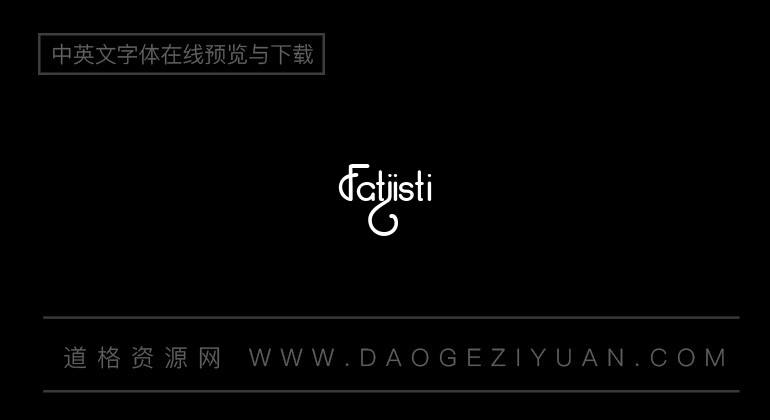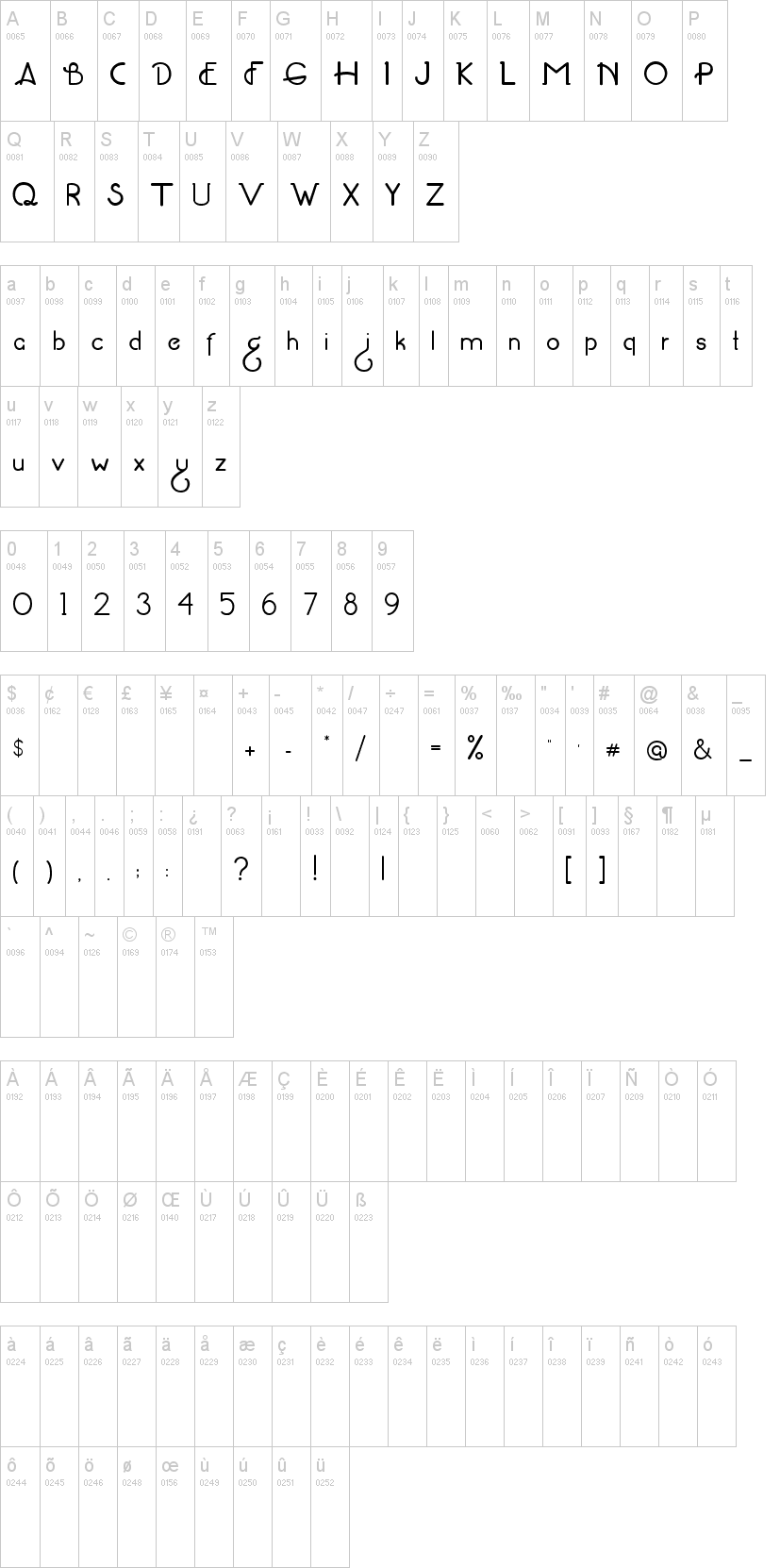
Fatjisti 字体是一款简洁、优雅的英文字体,它的特点是字体的线条粗细比较均衡,没有太多的变化,给人一种稳重、大气的感觉。Fatjisti 字体有英文、拉丁文、希腊文等多种字体,适用于报纸、杂志、网页、海报等多种场合。内容介绍
Fatjisti是一款非常不错的手写艺术字体,具有很好的视觉感,适合于文化类的宣传设计、商业类品牌的广告和产品包装设计以及个性化文字排版等较多场景。